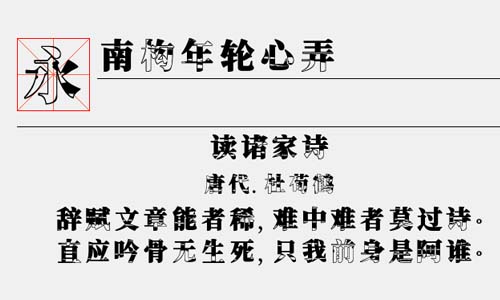
南構(gòu)年輪心弄是南構(gòu)字庫推出的一款個性藝術(shù)字體,個性醒目,具有強烈的視覺沖擊力,適應(yīng)于報紙和雜志和書籍中常用字體, 海報、個性促進品牌標(biāo)志設(shè)計、字體設(shè)計、等領(lǐng)域,歡迎喜歡南構(gòu)年輪心弄字體的朋友前來下載使用。